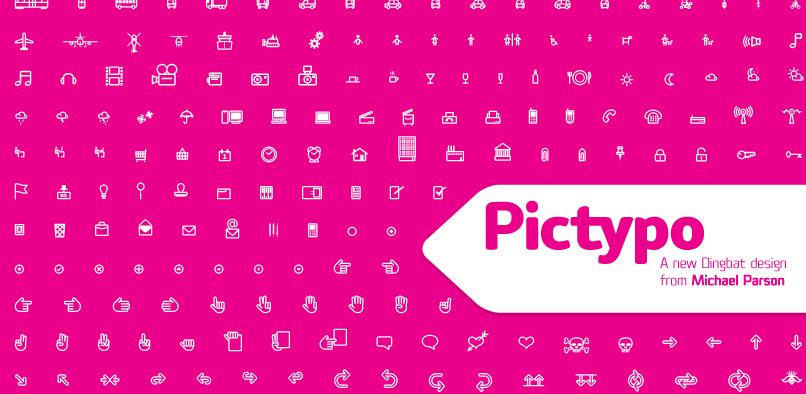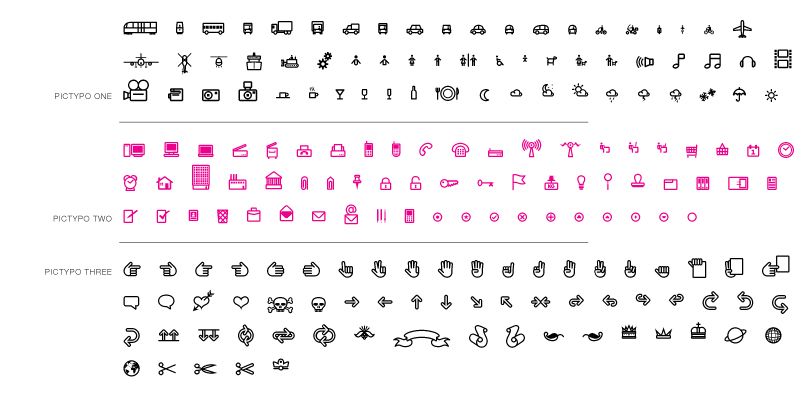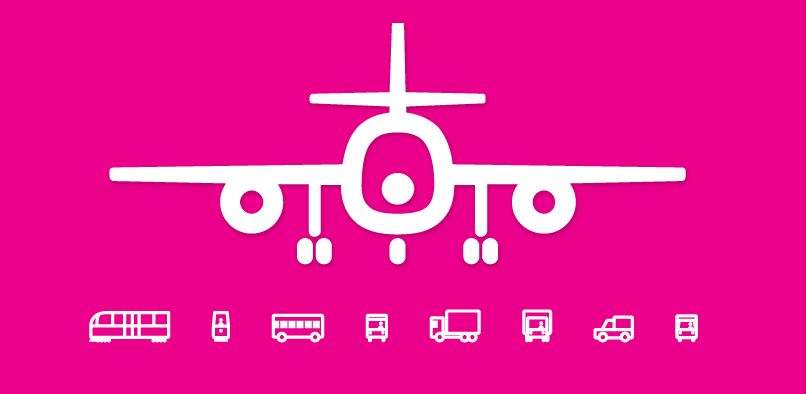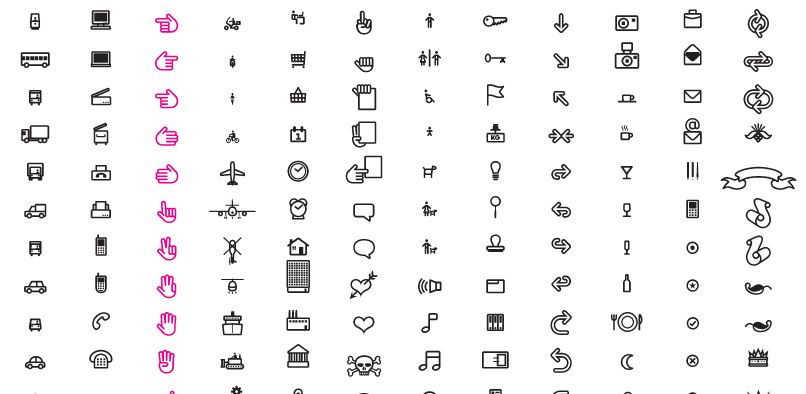
Pictypo Font family (2014)
Pictypo - это функциональный набор дингбатных шрифтов, созданных с открытым закругленным стилем, который содержит большой набор символов, от обычных стрелок, до метеорологических или офисных значков или мобильных устройств.